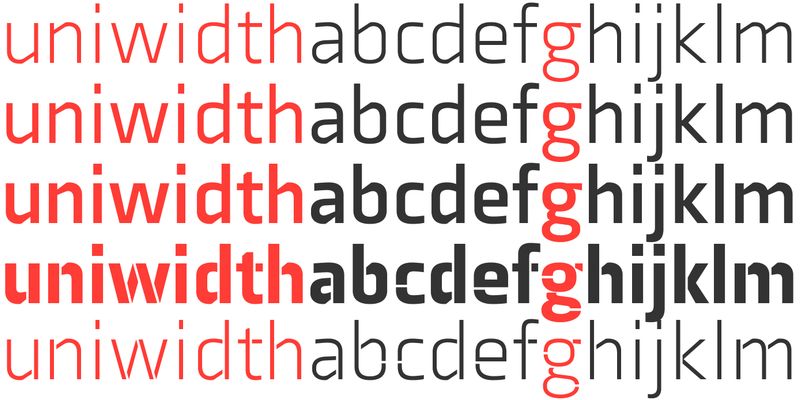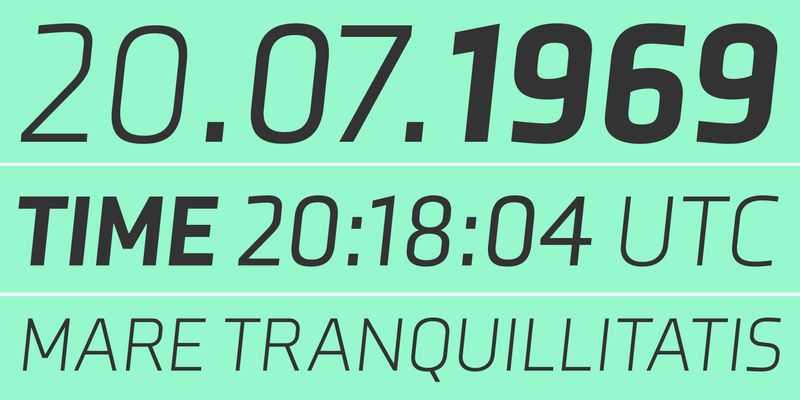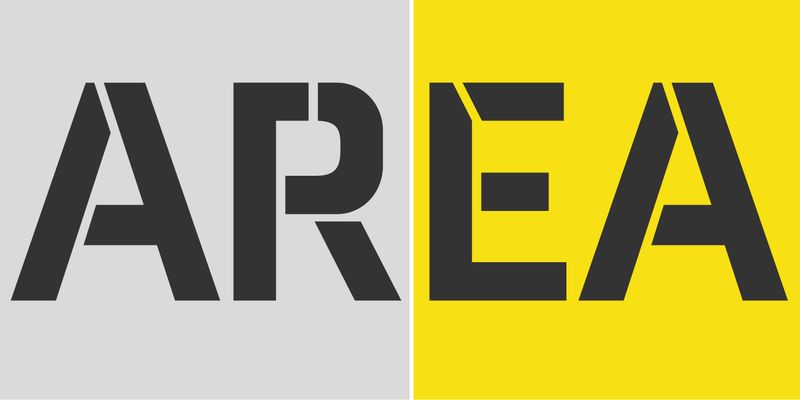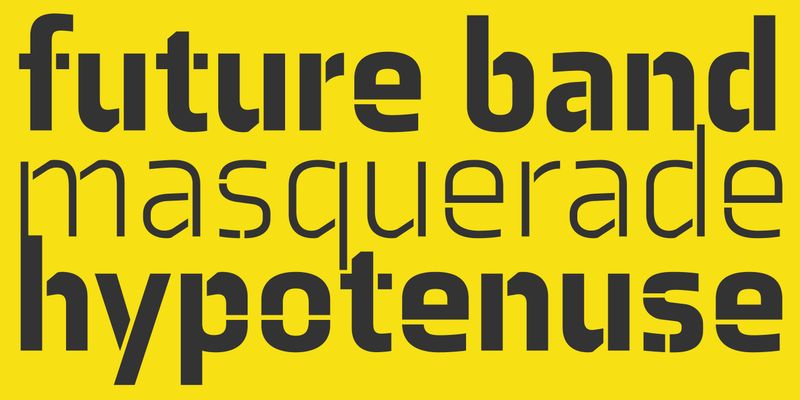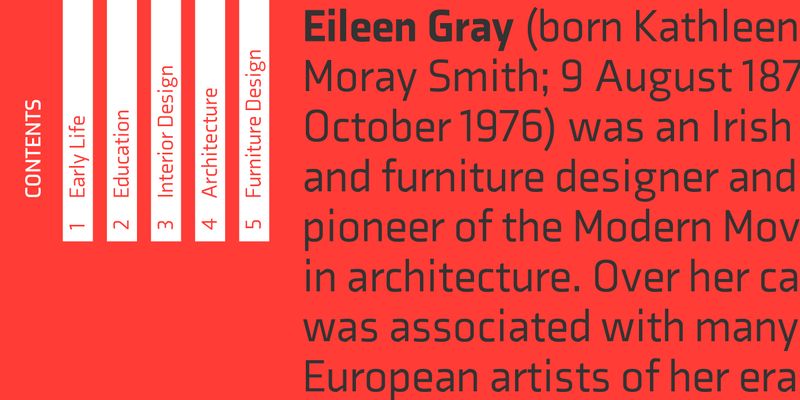
Axia es un sans serif de anchura única con formas de letra concisas. La tipografía consta de diez grosores de claro a negro, cada uno con cursiva y versalitas. Dos estilos para cartelería, Stencil Light y Stencil Black presentan una estética única. Una clara fragmentación de las letras le da a este diseño de plantilla su carácter particular. El tipo es perfecto para cautivar tamaños grandes; las formas de las partes flotantes abstractas atraen la vista y forman un tipo de letra de proporciones agradables cuando se unen.
Diseñado originalmente para la Escuela de Arquitectura de la Universidad de Rice en 2011, este sans contemporáneo encontró algo de inspiración en la familia tipográfica TwinCities creada por Sibylle Hagmann para la Universidad de Minnesota en 2003. Axia ha sido concebido desde cero, cada uno de los grosores romanos y cursivos armonizan perfectamente de ancho sin cambiar la longitud de la línea. El texto configurado en claro o negro da como resultado el mismo ajuste económico.
Los trazos arqueados internos del asta de la ‘b’ y la ‘d’ minúsculas, por ejemplo, abren progresivamente las formas de las letras y expresan claridad conceptual en todo el sistema. Una característica que cumple una doble función, contribuye a una gran legibilidad en grosores más altos y atribuye la versatilidad de los estilos individuales. Axia incluye muchas funciones OpenType y ofrece un amplio soporte de idiomas.